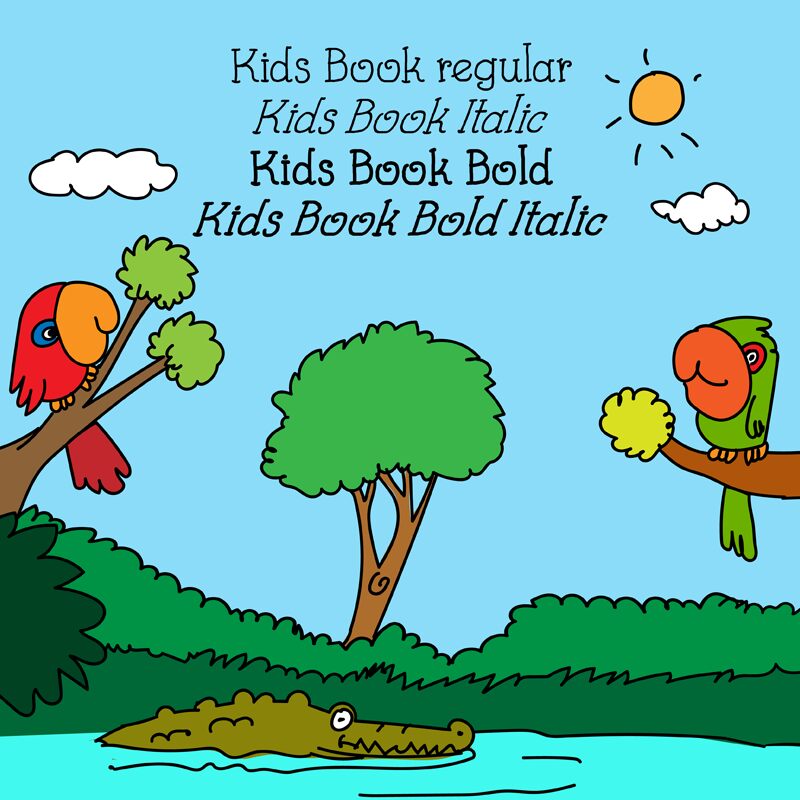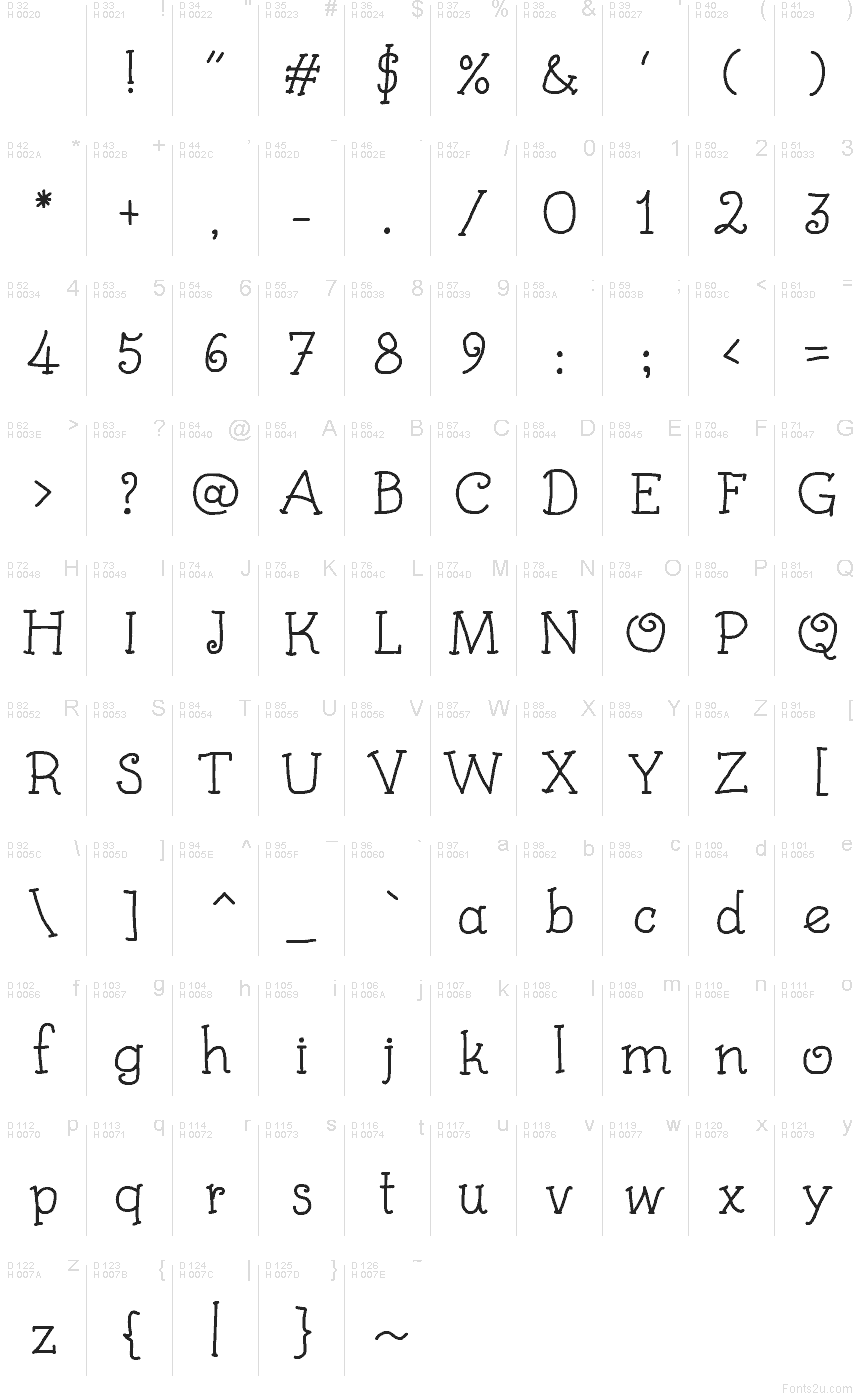
Kids Book od Galdino Otten je bezplatné ručně psané písmo, které připomíná rytmus pohádkových knížek a díky jemně nepravidelným tahům působí přirozeně a neformálně. Zaoblené konce a mírně kolísavé svislé tvary vytvářejí dojem, že bylo písmo kresleno přímo pro dětskou knížku, namísto aby působilo jako vyleštěný a neutrální font.
Skvěle se hodí na obálky dětských knih, školní plakáty, čtenářské deníky, narozeninové pozvánky i kreativní štítky. Nejlépe vynikne v krátkých nadpisech a jménech, protože hravý rytmus a měkké zaoblené zakončení dodávají textu vřelý a dětský tón, aniž by působilo příliš přeslazeně.